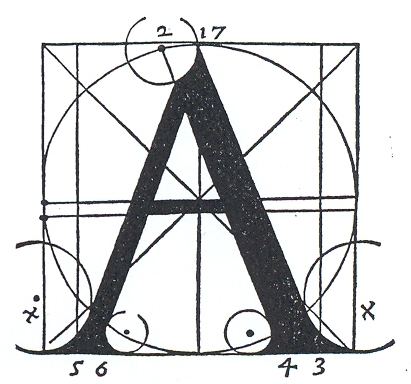
ПОСТРОЕНИЕ ШРИФТОВ
Даже самая несложная надпись требует построения и
предварительного расчета. При построении надписи
необходимо определить верхние и нижние границы стро¬
ки, разбить в строке ширину букв, промежутки между
ними и словами. В ряде случаев в строке проводятся до¬
полнительные линии для средних элементов букв
(рис. 48). На этом обычно построение заканчивается.
Дальше прорисовываются буквы, которые покрываются
краской или фиксируются каким-либо другим способом. Су¬
ществует даже специальный термин — рисованный шрифт,
обозначающий шрифт, выполненный вручную в отличие
от типографских печатных шрифтов.
Рисование шрифта с минимальным объемом предвари¬
тельных построений вполне удовлетворяет требованиям,
предъявляемым к большинству надписей, выполняемых от
руки (плакатные надписи, лозунги, объявления, таблицы
и др.).
В более серьезных работах, требующих более точного
воспроизведения рисунка каждой буквы, этих предвари¬
прибегают к ряду дополнительных построений, выполняемых
с помощью линейки и циркуля.
К таким построениямотносится проведение прямолинейных главных и соедини¬
тельных элементов, отложение при помощи измерителя
их ширины, использование циркуля в тех случаях, когда
кривые элементы букв проводятся по дугам окружностей.
Все остальные элементы более сложного начертания (ова¬
лы, многоцентровые кривые, спирали, сопряженные дуги
двойной кривизны и др.) рисуются от руки.
В ряде случаев, например при подготовке мемориальной
буется всю надпись выполнить с помощью точных геоме¬
трических построений. Это необходимо делать по ряду при¬
чин.
Во-первых, точное построение букв в надписи делает
ее наиболее удобочитаемой, четкой и закономерной.
При рисовании букв от руки почти невозможно достиг¬
нуть единообразия в начертании одной и той же буквы,
обеспечивающего четкость строки. Чтобы добиться этого,
часто прибегают к шаблонам. Но и в этом случае за счет
неточности расположения шаблона в строке получается не¬
которое «биение».
Рис. 48. Простейшая разбивка строки
а—верхняя линия строки; б—высота букв; в—средние линииГстроки;
г—нижняя линия строки; д—ширина буквы; е—промежуток между словами;
ate—промежуток между буквами; а—промежуток между строками
Рис 49. Пример одновременного применения
нескольких средних линий
Существует много альбомов с таблицами различных
шрифтов. В редких случаях приведенный шрифт сопро¬
вождается построениями. Это уменьшает ценность подоб¬
ных таблиц. При перерисовке букв, как правило, утрачи¬
ся пропорции, изменяется контрастность. При многократ¬
ной последовательной перерисовке от образца мало что
остается.
Другое дело, если шрифт имеет построения. Его форма
закреплена построениями подобно тому, как состав какого-
либо химического вещества закреплен формулой.
Буквы, имеющие построения, могут быть легко воспро¬
изведены человеком, мало искушенным в графике. По¬
строение дает возможность точно воспроизвести букву в
любом масштабе, что очень трудно сделать, имея образец
рисованной буквы.
При точном построении букв надпись всегда выглядит
более строгой и чистой. Однако точное построение букв
часто игнорируется. В большинстве случаев это про¬
исходит от незнания художником необходимых геометри¬
ческих основ и неумения применить их в практической
работе.
Шрифты, приведенные в таблицах настоящей книги,
сопровождаются построениями. Однако далеко не все из
приведенных шрифтов были построены их авторами. Для
многих этих шрифтов построения были восстановлены, а
для большинства — созданы заново. Шрифты, имевшие
точные построения, воспроизведены здесь без каких бы то
ни было изменений (табл. 19, 24, 25, 26, 27).
Не следует, однако, умалять значения свободного рисо¬
Только рисунок дает свободу в поисках необ¬ходимых форм. Роль построения заключается в том, чтобы
вначале дать основу для этого рисунка, а после уточнить
его формы и закрепить их.
По точности пропорций и тонкости рисунка начертания
букв родственны архитектурным формам. Простота и лако¬
ничность рисунка букв требуют большой точности его пост¬
роения.
Так же как и построение архитектурных форм, построе¬
ние начертаний букв базируется на строгой геометрической
основе.
Исходным элементом этой основы является строка, верх¬
няя и нижняя линии которой определяют высоту букв и
Эти линии, как правило, являются прямыми и парал¬
лельными, хотя в отдельных случаях применяют и другую
форму строк.
Основным элементом построения букв является сред¬
няя линия строки, положение которой зависит от приня¬
того членения букв по высоте. Средняя линия определяет
положение поперечных элементов букв.
Как правило, эта
линия проходит несколько выше середины строки. Иногда